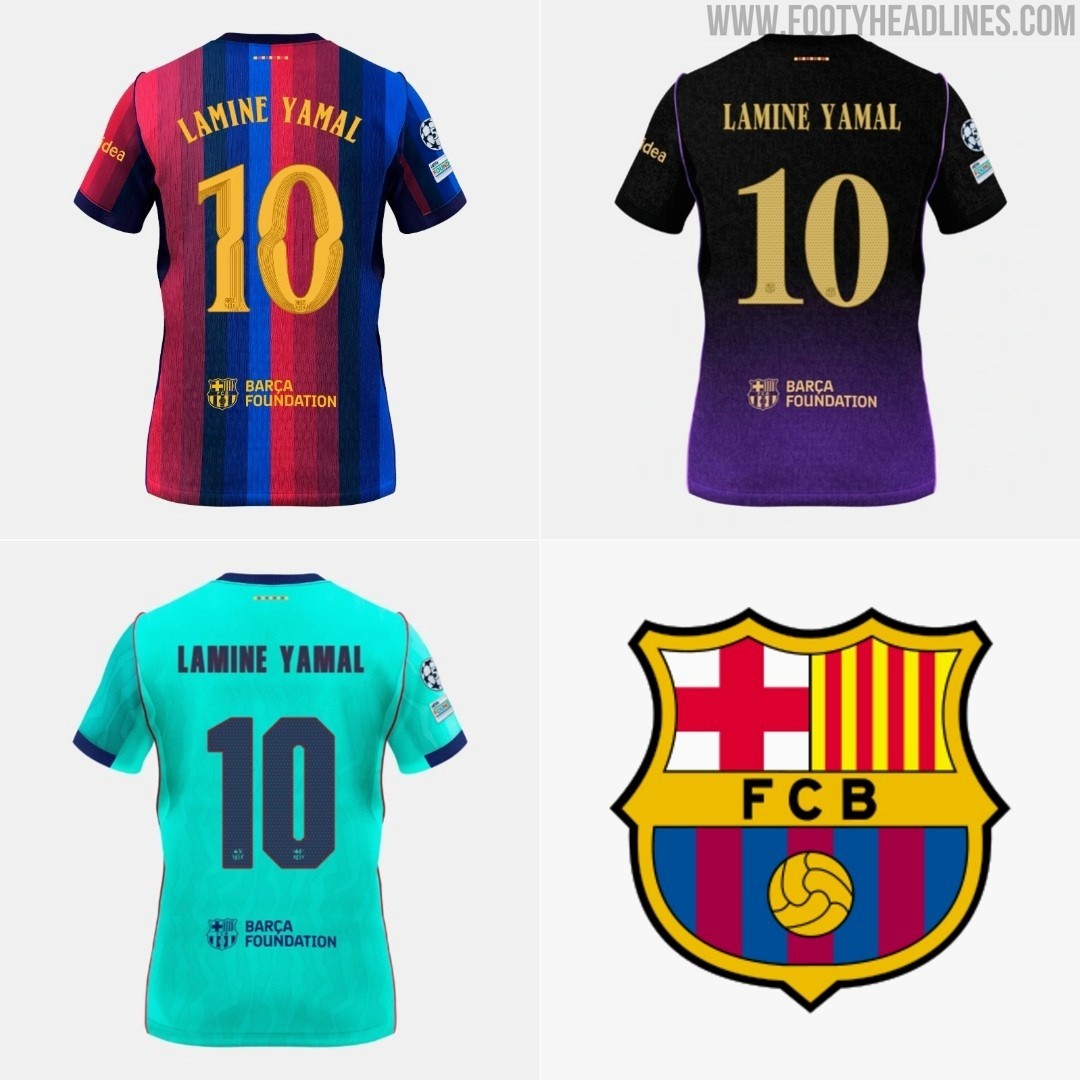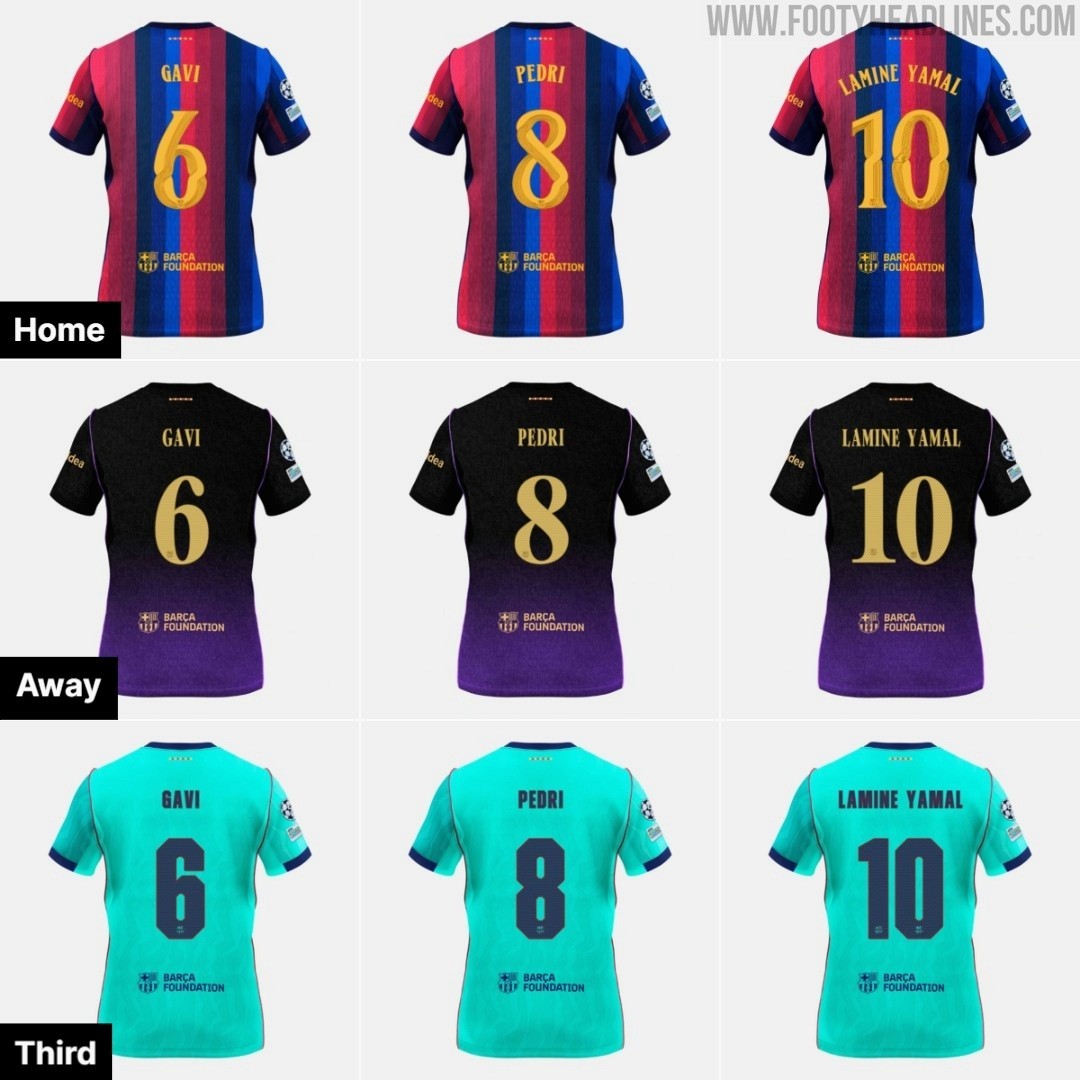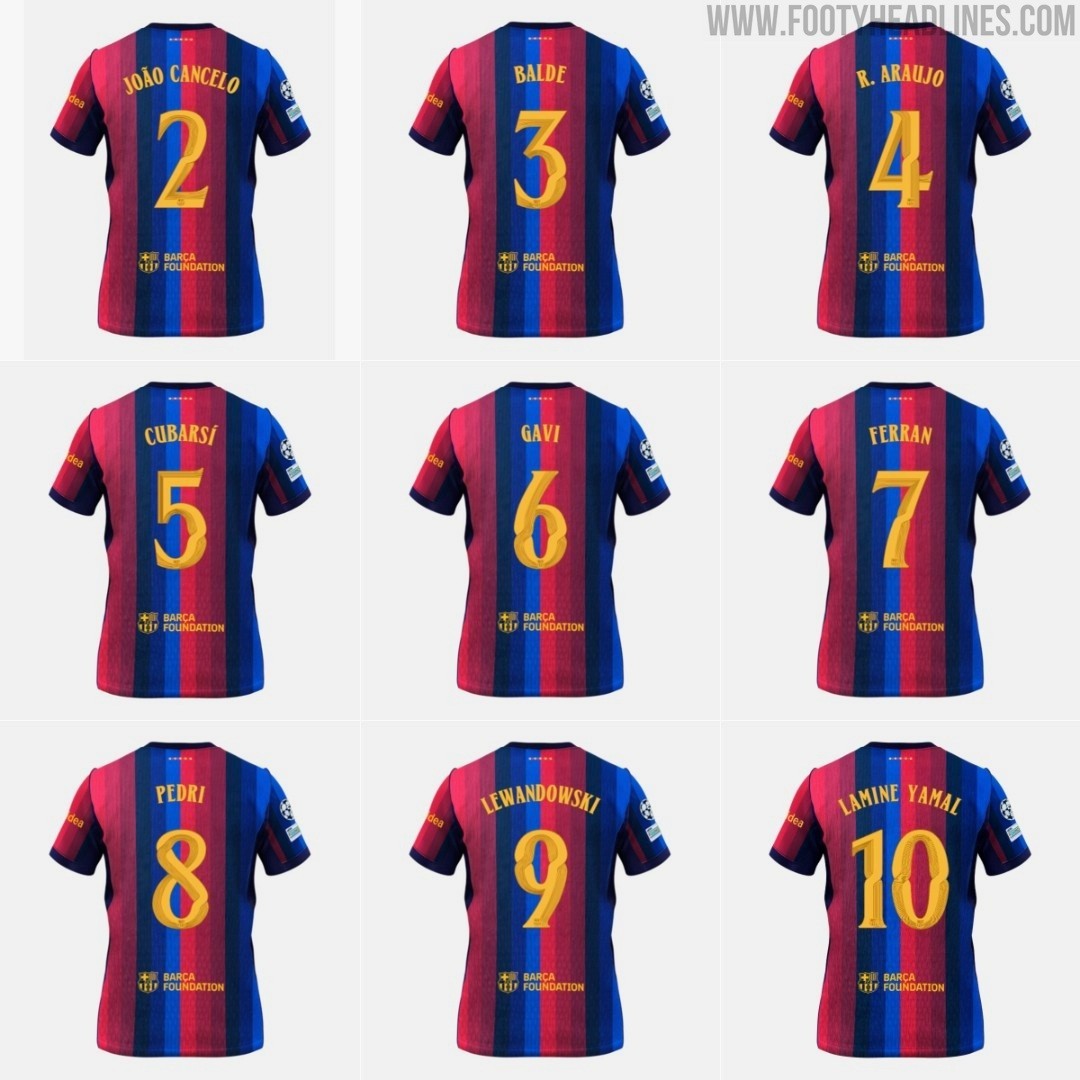
Se han presentado tres tipografías personalizadas para las camisetas locales, visitantes y de tercera del FC Barcelona para la temporada 26-27
• Cambio de Tipografías: El FC Barcelona ha introducido tres nuevas tipografías personalizadas para sus camisetas local, visitante y tercera de la temporada 26-27, rompiendo con el uso de la misma fuente durante siete temporadas.
• Tipografía de la Camiseta Local: La tipografía de la camiseta local se aleja de los diseños deportivos estándar, incorporando líneas artísticas inspiradas en el movimiento del Modernisme Català.
• Tipografía de la Camiseta Visitante: La tipografía de la camiseta visitante presenta un intenso color dorado metalizado que crea contraste con el fondo oscuro y complementa los ribetes y logotipos dorados de la equipación.
Tras siete temporadas seguidas utilizando el mismo conjunto de fuentes, el FC Barcelona ha dado un giro impresionante al presentar tres tipografías totalmente nuevas y personalizadas, cada una diseñada especialmente para la camiseta local, la camiseta visitante y la tercera camiseta de la temporada 2026-27.
Tipografías de las camisetas del FC Barcelona 26-27: 3 ediciones
Se han presentado tres tipografías personalizadas para las camisetas locales, visitantes y de tercera del FC Barcelona para la temporada 26-27
Las nuevas tipografías de las camisetas del FC Barcelona 26-27 vienen en tres versiones distintas, adaptadas específicamente a cada camiseta. Mientras que las tipografías de las camisetas local y visitante presentan un diseño suave y fluido con curvas elegantes, la tipografía de la tercera camiseta tiene un estilo más angular y rectilíneo.
Tipografía de la camiseta local del FC Barcelona 26-27
La nueva tipografía de la camiseta local del FC Barcelona 26-27 se aleja por completo de la tipografía deportiva estándar, de trazos gruesos, e introduce líneas artísticas profundamente inspiradas en el famoso movimiento del Modernisme Català (arquitectura modernista catalana).
Se presenta la nueva tipografía de la camiseta del FC Barcelona 26-27, inspirada en la arquitectura catalana
La tipografía de la camiseta visitante del FC Barcelona 26-27
La nueva tipografía de la camiseta visitante del FC Barcelona 26-27 presenta un intenso color dorado metalizado. Este vibrante tono dorado crea un gran contraste con el fondo oscuro en negro y morado de la camiseta, y combina a la perfección con los ribetes dorados de las mangas, los logotipos de los patrocinadores y el escudo del club en la parte delantera.
Se presenta la nueva tipografía de la camiseta visitante «Gold Mamba» del FC Barcelona 26-27
Tipografía de la tercera camiseta del FC Barcelona 26-27
La nueva tipografía de la tercera camiseta del FC Barcelona para la temporada 2026-2027 presenta una estética claramente moderna y estructurada que la distingue del resto de la colección del club para la temporada 2026-2027.
Se presenta la nueva tipografía de la tercera camiseta del FC Barcelona 26-27